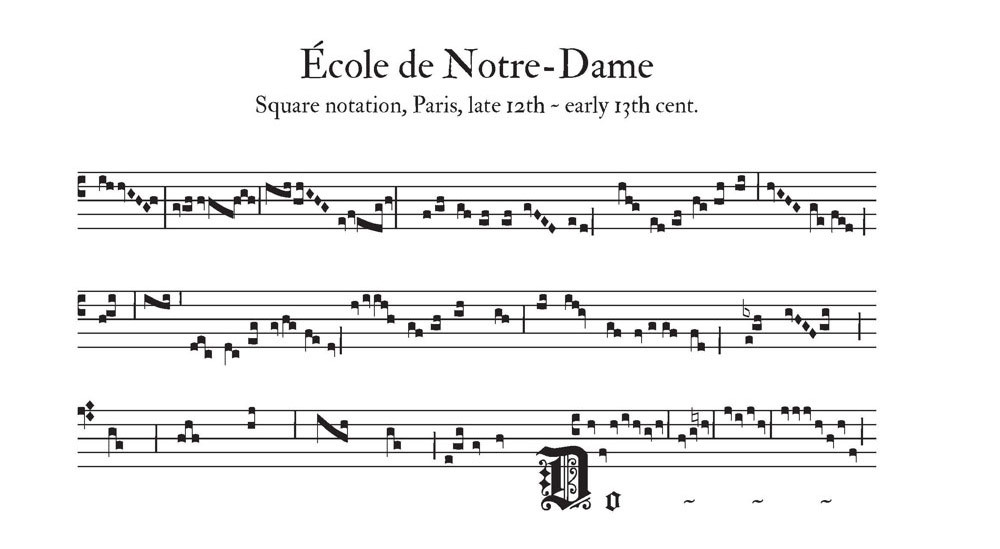
La notazione della musica medievale è straordinariamente ricca e complessa ed il software Medieval v.1, realizzato originariamente nel 1999, è stata la prima soluzione disponibile per copisti, studenti, specialisti – e semplicemente per gli amanti della musica – per realizzare spartiti di musica medievale in modo professionale.
Il tanto atteso Medieval 2 ha ora un codice completamente nuovo, così come un nuovo look, nuova documentazione e molte nuove funzionalità.
Medieval 2 per Finale, l’unica vera soluzione per tutti coloro che si dedicano alla notazione di musica antica, straordinariamente varia e complessa.
La notazione della musica medievale è straordinariamente ricca e complessa ed il software Medieval v.1, realizzato originariamente nel 1999, è stata la prima soluzione disponibile per copisti, studenti, specialisti – e semplicemente per gli amanti della musica – per realizzare spartiti di musica medievale in modo professionale.
Il tanto atteso Medieval 2 ha ora un codice completamente nuovo, così come un nuovo look, nuova documentazione e molte nuove funzionalità.
Medieval 2 offre la possibilità di produrre trascrizioni professionali di musica antica, dalla notazione Gregoriana alla tarda notazione Medievale, con un rendering professionale ed un’incredibile attenzione al dettaglio.
E naturalmente Medieval 2 sfrutta appieno la potenza di Finale per l’impaginazione, la precisione grafica e la stampa.
Medieval 2 ti fornisce una vasta gamma di strumenti dedicati per la gestione di neumi, di liquescenze, per la gestione delle guide, dei quilisma , dei gruppi di note, e ti fornisce numerosi simboli speciali: oriscus, pause, plica, legature, black-void (white) notation, etc.
E lo strumento unico Neuma Tool è uno strumento automatico è così avanzato in termini di design e funzionalità che è più di un plug-in e può essere considerato un software all’interno di un software, ed ha la gestione di oltre 200 diversi neumi.